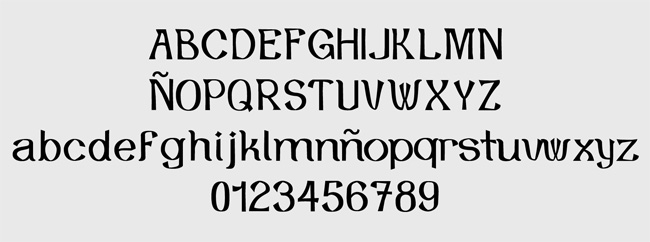
Esta tipografía nació como fruto de un taller impartido por Dinamo.us. La idea del taller era diseñar cinco caracteres mediante la interpolación de los mismos. Esos cinco caracteres se convirtieron más tarde en una fuente tipográfica completa con características variadas.
Los caracteres tienen trazos irregulares, como si estuviesen esculpidos en piedra y son frutos de una interpolación entre dos objetos.
Ha sido diseñada por Peter Kocur, diseñador de branding y de producto afincado en Bratislava, Eslovaquia.
This typography was born as a result of a workshop given by Dinamo.us. The idea of the workshop was to create five letters through interpolation. These five characters later became a complete typographical font with varied characteristics.
The characters have irregular strokes, as if they were sculpted in stone and are the result of an interpolation between two objects.
It has been designed by Peter Kocur, product and branding designer settled in Bratislava, Slovakia.